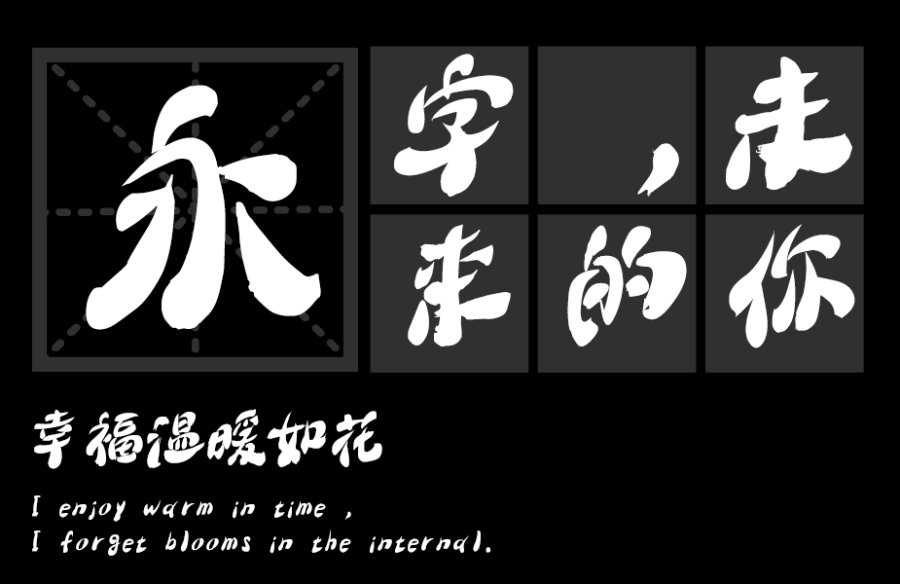
大梁繁简精全字体发布
字体名称:大梁繁简精全
字体类别: 毛笔书法
大梁繁简精全字体简介:著名书法家大梁(北京徐悲鸿纪念馆主任),历时8年毛笔书写的25000字的繁简精全大字库,笔画具有独具风格特点,央视及各卫视都在应用,全国各地的大德中国结为大梁体。具有独具特色的书法意境。
大梁繁简精全预览图展示: